모노타입이 선정한 2025년 폰트 트렌드 “개인화부터 넷제로까지”
모노타입 2025 폰트 트렌드 보고서 정리
글로벌 폰트 및 폰트 기술 전문 기업 모노타입(Monotype)이 2025년 폰트 트렌드 보고서를 공식 발표했다. 모노타입의 폰트 트렌드 보고서는 매년 디자이너와 브랜드 마케터들에게 필수적인 자료로 자리 잡았다. 현재 모노타입 폰트 트렌드 보고서는 디자인 커뮤니티에서도 큰 인기를 끌며, 주요 브랜드 및 크리에이티브 전문가들이 참고하는 주요 리소스다.
특히 올해 보고서는 한글 번역본이 영어 원문과 동시에 공개돼 한국의 디자인 및 브랜드 전문가들에게도 보다 신속하고 깊이 있는 인사이트를 제공하고 있다. 이번 보고서는 폰트가 디자인과 브랜드 경험의 중심 요소로 자리 잡고 있음을 강조하며, 더욱 심도 있는 통찰과 전략적 방향성을 제시한다.
또한 올해 보고서는 과거 트렌드 보고서들과 비교해 타이포그래피가 인공지능, 사회적 변화, 환경, 정치 및 멀티미디어와 어떻게 교차하는지를 분석한 것이 특징이다.
개인화된 경험
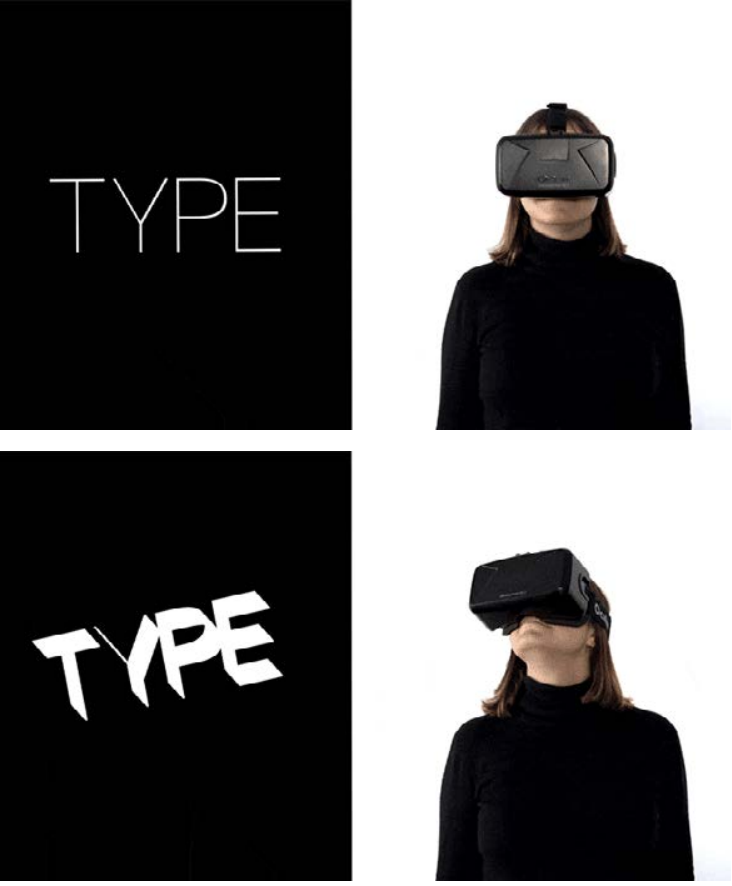
인공지능(AI)이 디자인 산업의 흐름을 혁신적으로 변화시키고 있는 만큼 모노타입 역시 올해 폰트 트렌드 중 하나로 AI를 사용한 ‘개인화된 경험’을 키워드로 꼽았다. 특히 모노타입은 “AI가 폰트를 생성하고 최적화하는 과정을 심층적으로 분석하는 동시에, 향후 디자이너가 AI를 활용한 타이포그래피로 독자 개개인에게 맞춤형 경험을 제공할 수 있게 될 것”이라 내다봤다.
또한 모노타입은 AKQA가 코카콜라를 위해 10만 장이 넘는 액체 거품 사진을 촬영한 후 AI를 활용해 제작한 거품 타이포그래피 캠페인, 누텔라가 알고리즘을 통해 700만 개가 넘는 병 디자인을 만들어낸 사례 등을 언급하며 AI로 폰트 디자인을 자동화하면서도 창의적인 가능성을 넓힐 수 있고, 이러한 기술의 발전이 디자이너의 역할을 어떻게 변화시키고 있는지를 조명했다.
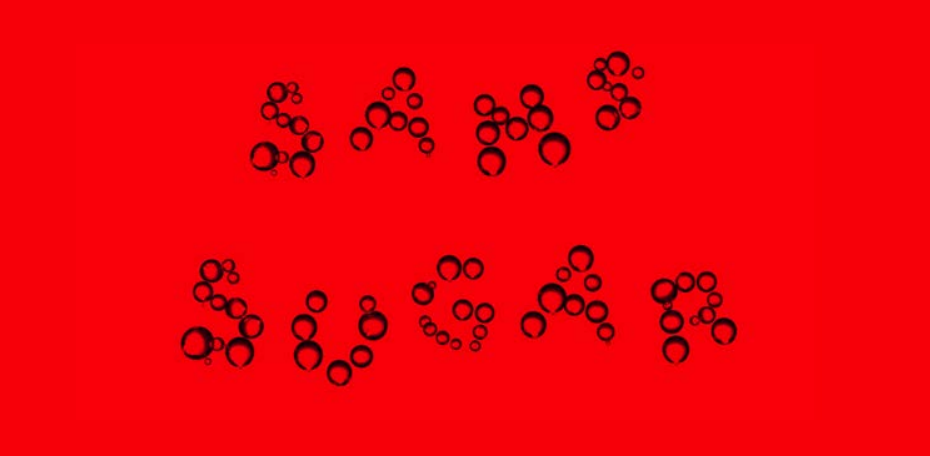
하지만 모노타입이 향후 모든 디자인 창작자의 작업을 AI가 대체할 것이라고 내다본 것은 아니다. 실제 모노타입은 “AI가 폰트를 만드는 방식, 사용하는 방법, 이해하는 과정을 크게 변화시킬 것은 분명하다. 하지만 중요한 점은 디자인로서 창작 과정에서 어떤 가치를 더할 수 있는지를 스스로 정의하는 것이다”며 AI의 발전에도 불구하고 인간 디자이너의 감성과 창의성이 여전히 필수적인 요소로 남아 있다는 점을 강조했다.
키네틱 타이포그래피
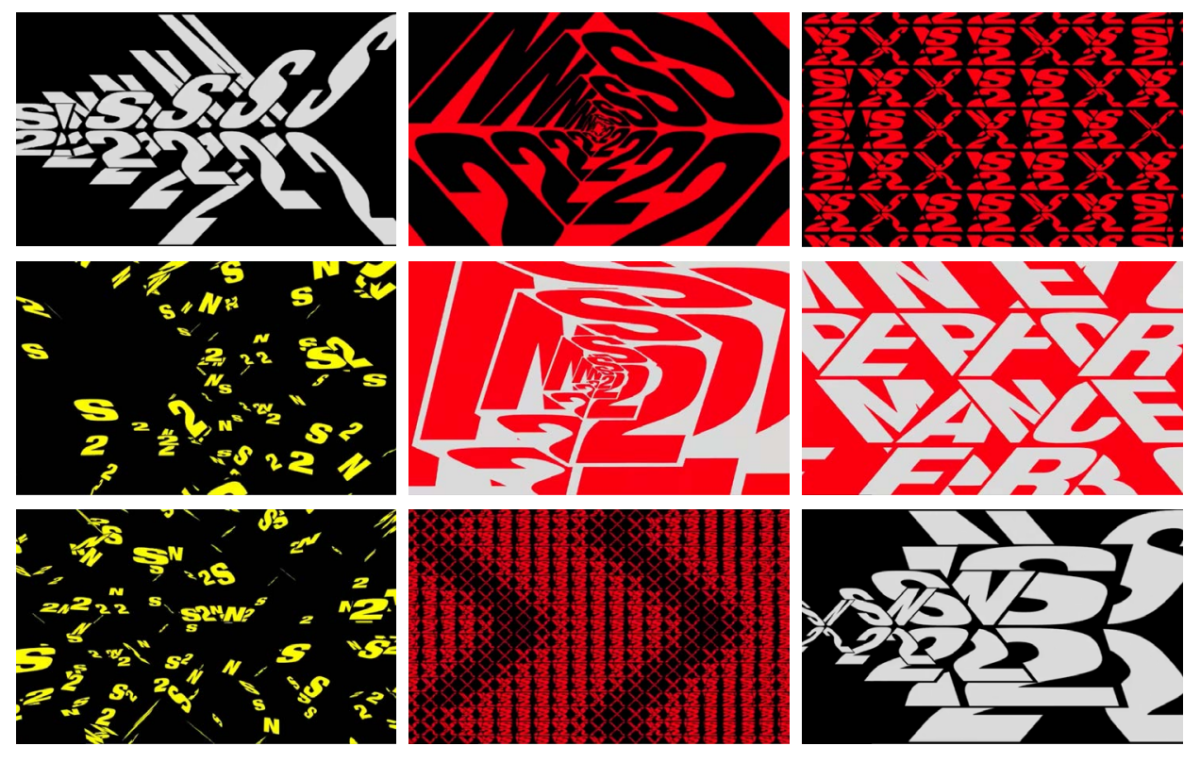
디지털과 멀티미디어 환경이 확장되면서 타이포그래피의 역할도 점점 더 중요해지고 있다. 소셜 미디어, 디지털 광고, 영상 콘텐츠 등에서 폰트가 활용되는 방식이 더욱 다채로워지고 있으며, 음성, 영상, 인터랙션과 결합된 다양한 사례를 통해 새로운 타이포그래피의 가능성이 탐구되고 있다. 이런 변화는 단순한 트렌드를 넘어 폰트가 현대적인 커뮤니케이션의 필수 요소로 자리 잡고 있음을 보여준다.
모노타입은 이런 변화 속에서 ‘키네틱 타이포그래피’를 올해의 폰트 트렌드 키워드 중 하나로 꼽았다. 디지털과 멀티미디어 환경이 확장되고, 타이포그래피가 단순한 디지털 환경의 표현 도구를 넘어 브랜드 아이덴티티를 형성해 사용자 경험을 개선하는 중요한 요소로 자리 잡고 있는 상황 속에서 키네틱 타이포그래피가 차별화에 도움이 될 것이란 이야기였다.
키네틱 타이포그래피는 움직이는 텍스트 또는 이를 기반으로 영상을 만드는 것을 뜻한다. 올해 모노타입은 이전 트렌드 보고서에서도 소개된 키엘 무첼크나우스가 설립한 스튜디오 DIA를 모션 타이포그래피의 선두주자로 지목해 다양한 작품을 소개했다.
사회적 계약
‘사회적 계약’ 트렌드 키워드는 타이포그래피가 법과 질서, 정치적 변화, 평등과 포용성 같은 이슈에서도 중요한 역할을 하며, 사회적 변화와도 밀접해 있다는 사실에 기반했다.
실제 모노타입은 “법률 문서를 폰트로 정리하고, 선거 과정은 강렬한 타이포그래피로 표현된다”며 “항의 팻말 신문 사설, 바이럴 영상, 시위 계획, 시, 항의 노래의 가사 등 역시 타이포그래피로 자유를 표현하고, 협상하며, 되찾는 모든 순간을 시각적으로 담아내는 도구로 활용된다”고 키워드 선정 이유를 설명했다.
특히 모노타입은 FC 장크트파울리 축구 클럽을 위해 만들어진 ‘FC 산스 파울리(FC Sans Pauli)’ 폰트를 관용, 다양성, 사회적 정의 등 ‘태도가 담긴 폰트’의 모범적인 예시로 들며, 폰트가 사회적 메시지를 전달하는 강력한 도구로 활용될 수 있음을 강조했다.
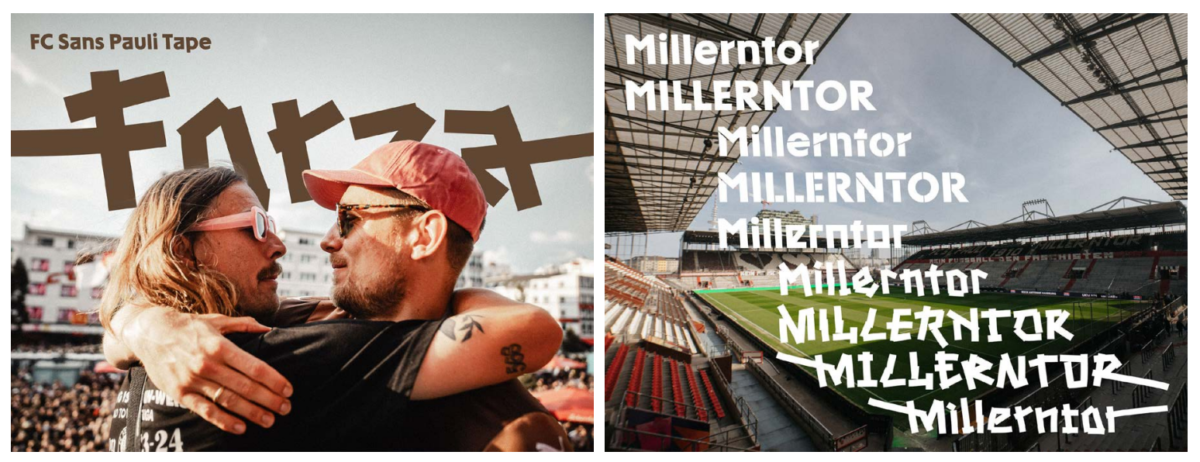
노화와 시각 장애
지난해 12월 23일 기준 국내 65세 이상 노인 인구가 1000만이 됐고 행안부가 공식적으로 초고령화 사회 진입을 선언한 만큼, 전체 인구 저출산 및 고령화 문제는 더 이상 먼 미래의 이야기가 아니다. 이러한 변화 속에서 다양한 연령층이 글을 읽고 이해하는 방식이 서로 다르다는 점도 고려해야 한다. ‘노화와 시각 장애’는 이런 트렌드를 반영한 키워드다.
실제 모노타입은 “인구 구성은 고령화 사회로 나아가고 있으며, 미디어 환경도 빠르게 바뀌어 나가고 있다”며 “이에 맞춰 폰트, 폰트 기술, 그리고 이를 활용하는 디자이너도 다양한 독자의 요구와 변화에 발맞춰 진화해야 한다”고 말하면서 트렌드 선정 사유를 설명했다.
이외에도 모노타입은 인텔 원 모노(Intel One Mono), 렉센드(Lexend), 네임 산스(Name Sans) 등 다양한 가독성 중시 폰트를 소개하며 젊은 세대부터 노년층까지 각기 다른 읽기 습관과 요구를 반영한 폰트 스타일을 분석하고, 모든 연령대의 사용자가 쉽게 접근할 수 있는 디자인 전략을 논의함으로써 보다 포괄적인 커뮤니케이션 환경을 조성하는 방안을 제시했다.
넷 제로 타이포그래피
또한 모노타입은 지속 가능성이 디자인 업계의 중요 화두로 떠오르는 가운데, ‘넷 제로 타이포그래피’를 트렌드 키워드를 꼽으면서 친환경적인 폰트 디자인과 디지털 환경에서의 폰트 사용 방식에 대한 논의도 함께 다뤘다.
실제 모노타입은 잉크 사용량을 줄이기 위해 투명성을 활용한 폰트 ‘체빈 에코(Chevin Eco)’ 와 산돌이 지속 가능성을 브랜드 폰트에 담아내 제작한 ‘라인 시즈(LINE SEED)’ 폰트 등 폰트의 선택이 에너지 소비와 환경에 미치는 영향을 탐구하며, 디지털 시대에 적합한 지속 가능한 타이포그래피 전략을 제안하기도 했다.
아울러 모노타입은 제안 과정에 있어서도 “타이포그래피는 행동을 촉구하고, 사고방식을 바꾸며 더 나은 미래를 상상하도록 도울 수 있다”며 “넷 제로를 실형하는 과정은 쉽지 않지만 우리가 선택할 수 있는 미래는 더 친환경적이고 깨끗해야만 한다. 다른 대안은 없다”며 타이포그래피를 앞세운 친환경 디자인 전환을 촉구했다.
올해 더 깊은 탐구를 예고한 모노타입
이번 보고서는 단순히 유행하는 폰트를 나열하지 않고, 폰트가 우리의 커뮤니케이션 방식과 브랜드 정체성에 미치는 영향을 폭넓게 분석하는 데 중점을 두었다.
찰스 닉스 모노타입 수석 총괄 크리에이티브 디렉터는 “이번 보고서는 디자인과 창의성이 글로벌 문제 해결에 어떻게 기여하며, 빠르게 변화하는 사회와 기술 환경 속에서 어떤 역할을 하는지를 보여주는 자료다”며 “이를 통해 디자이너와 크리에이터들이 협력하여 변화하는 세상에서 미래의 시각 문화를 형성하는 데 영감을 얻을 수 있기를 바란다”라고 말했다.
향후 모노타입은 크리에이티브 파트너들과 협력해 올해 보고서에서 다룬 주요 주제를 더욱 심도 있게 탐구할 예정이다. 또한 이를 통해 타이포그래피가 어떻게 표현되고 발전하는지, 그리고 크리에이터들과 시각 문화가 글로벌 트렌드에 어떤 영향을 미치는지를 분석할 계획이다.